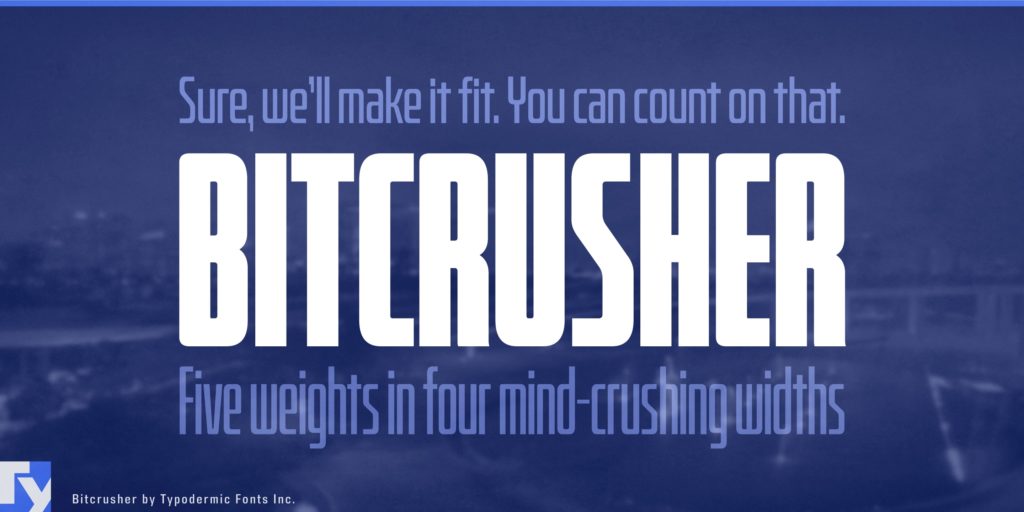
это уникальный гипер-сжатый гротеск от студии Typodermic Fonts. Его главная особенность — экстремальная узость начертаний (Condensed, Compressed, Crammed, Crushed), разработанная для размещения большого объема текста в тесных пространствах без потери читаемости. Строгая геометрическая форма букв сочетает техническую дисциплину с легкой мягкостью краев, что придает шрифту современный и технологичный вид. Он отлично работает в заголовках, где нужно привлечь внимание, и в плотной верстке. Скачать кириллическую версию бесплатно можно по ссылке ниже.